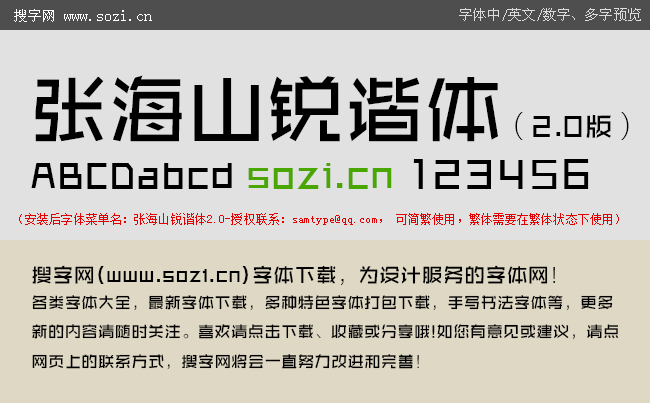
張海山銳諧體2.0
搜字網(wǎng)給大家提供一款很精致的張海山銳諧體2.0下載。張海山銳諧體是一款應(yīng)用于設(shè)計(jì)方面的中文簡(jiǎn)體漢字,字體呈方形,端正大方,結(jié)構(gòu)清晰,風(fēng)格統(tǒng)一,張海山銳諧體2.0字體比第一版增加了部分字符,可應(yīng)用于平面廣告、印刷包裝、廣告創(chuàng)意、網(wǎng)頁(yè)設(shè)計(jì)等領(lǐng)域。(注:此款與本站另一款張海山銳諧體銷有區(qū)別)